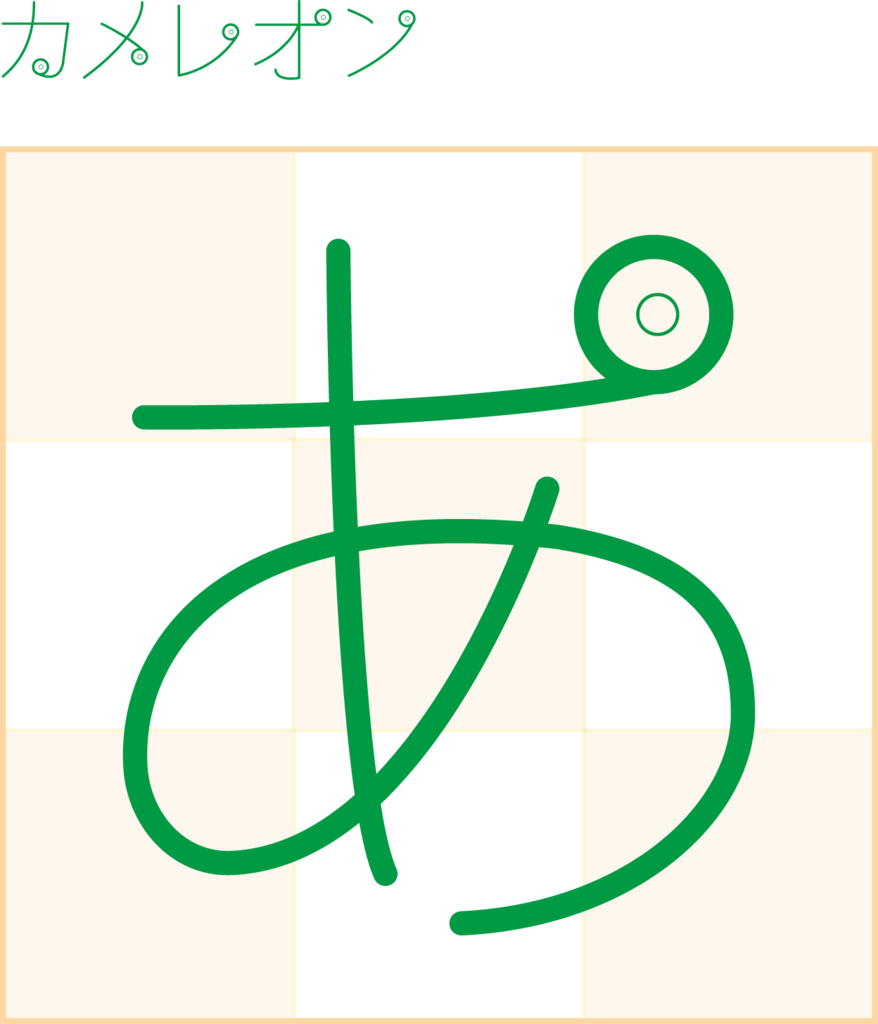
mojiruフォント「カメレオン」
mojiruフォントとしてタイ語と丸ゴシックをベースにフォントを作成してみた。
カメレオン「あ」の文字
カメレオン「トムヤムクン」の文字
トムヤンクンではgoogle翻訳で変換できなかったタイ文字だが、トムヤムクンなら変換できた。
またトムヤムクンという片仮名とタイ文字をmojiruフォント「カメレオン」で作成してみた。
次回は数字を作成しようと思う。